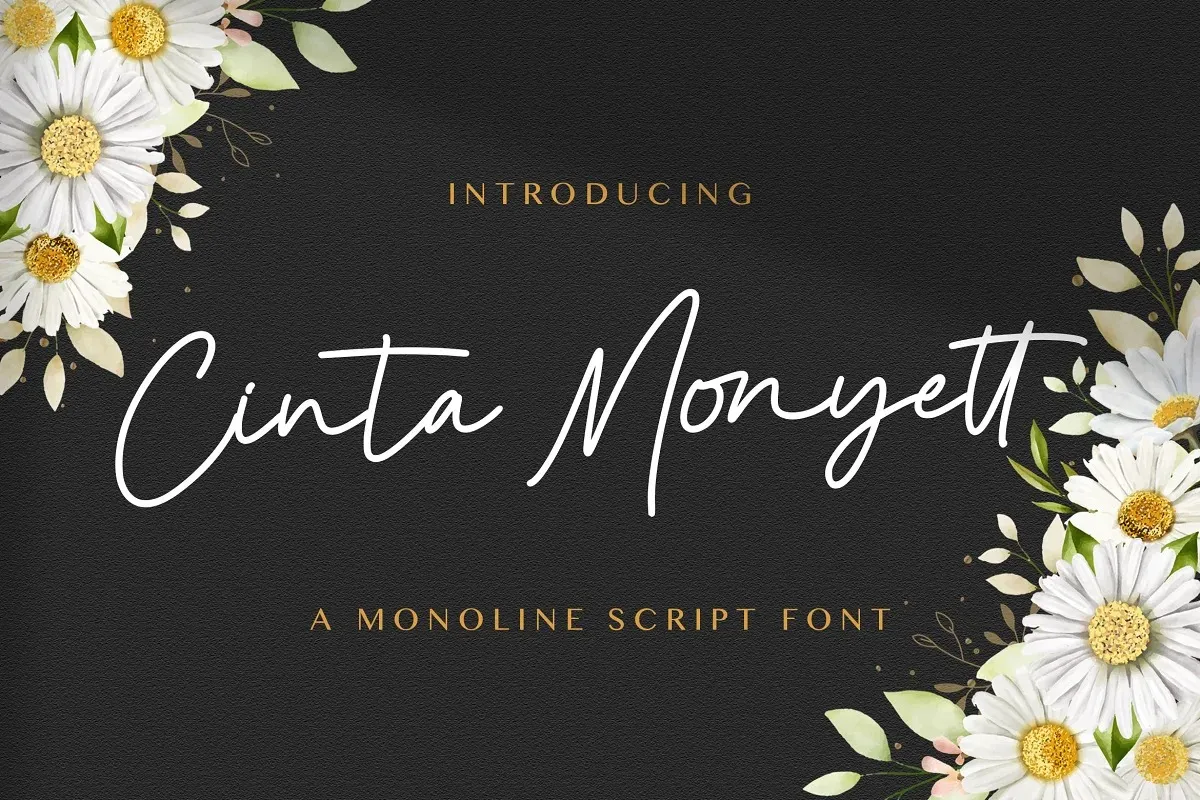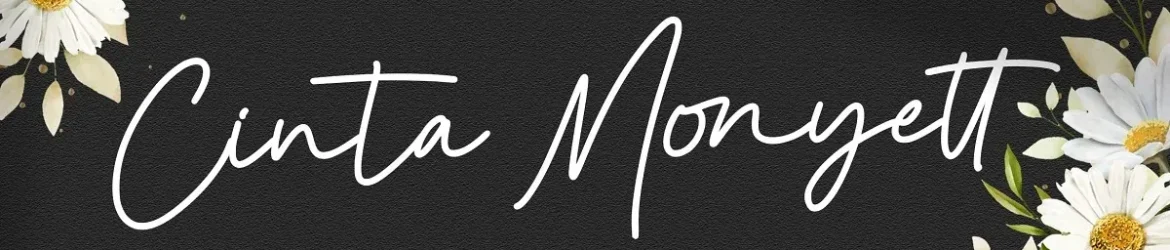
Cinta Monyett Font – Download Grátis
A Cinta Monyett Font é uma elegante escrita a mão com conceitos modernos de moda, criada pelo StringLabs. Seu design atemporal e bem equilibrado faz dela uma escolha perfeita para qualquer tipo de projeto gráfico ou design digital. Com seu charme feminino e classe clássica, essa fonte se adapta a muitas ideias criativas, tornando-as mais atrativas. Se você busca um toque único que enriqueça seus projetos, esta é a escolha perfeita para deixar suas criações ainda mais vivas e vibrantes. Experimente a Cinta Monyett Font em seu próximo projeto e descubra como ela pode dar uma nova vida aos seus esboços de design.